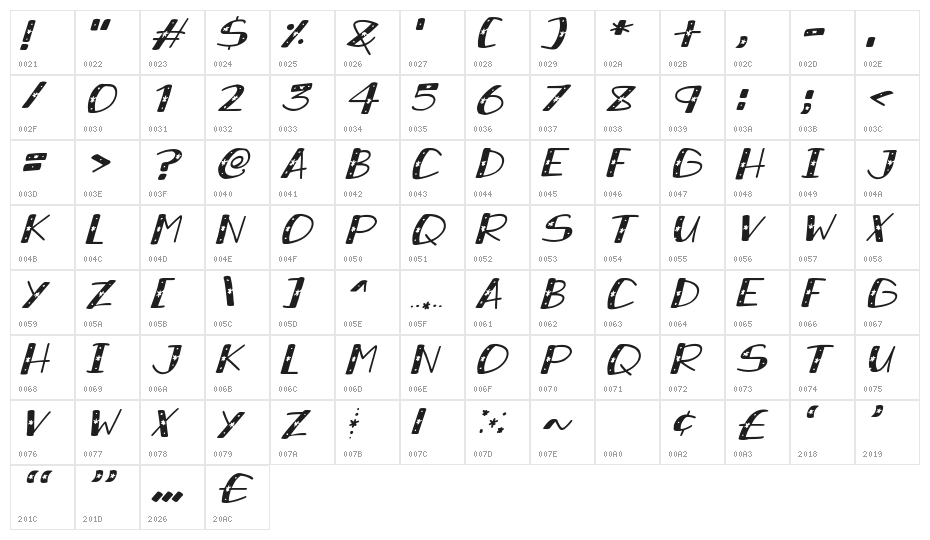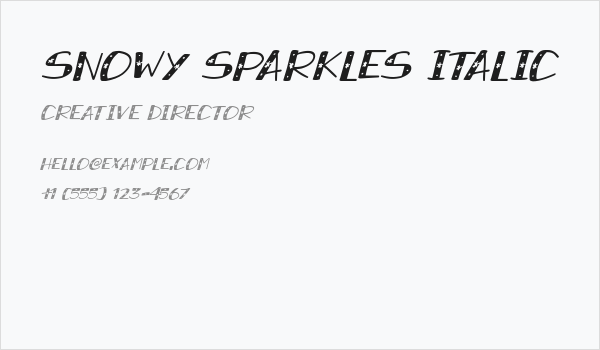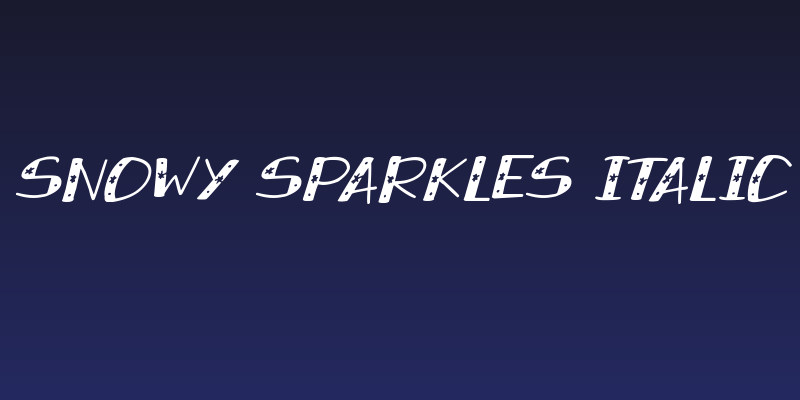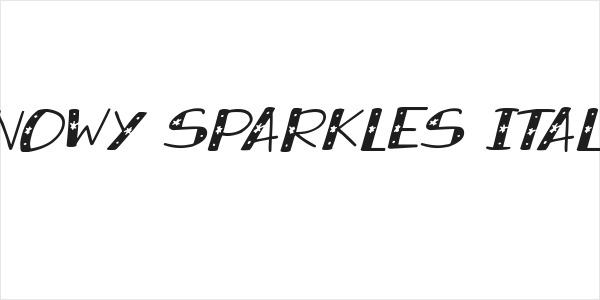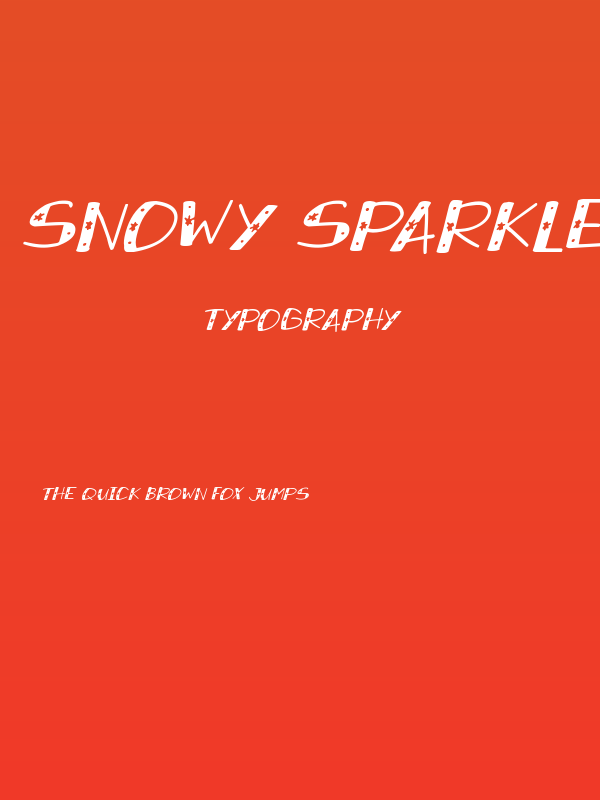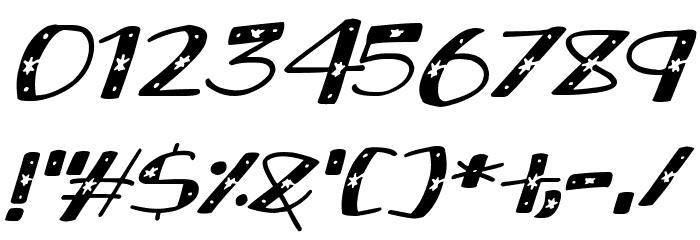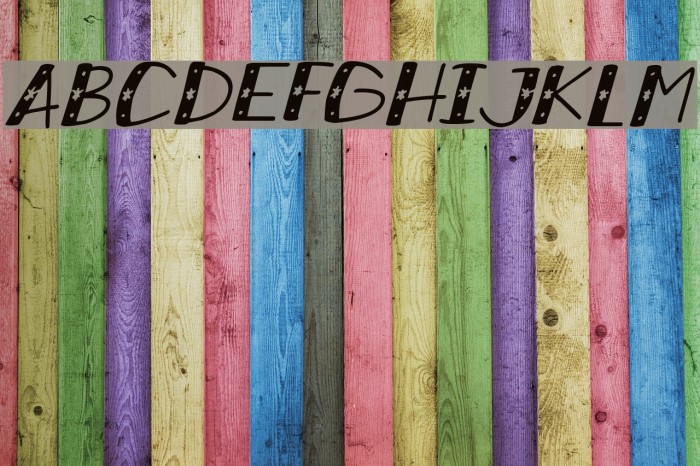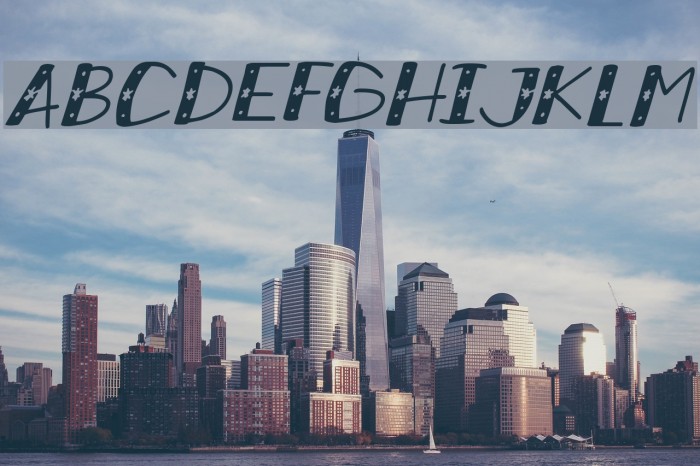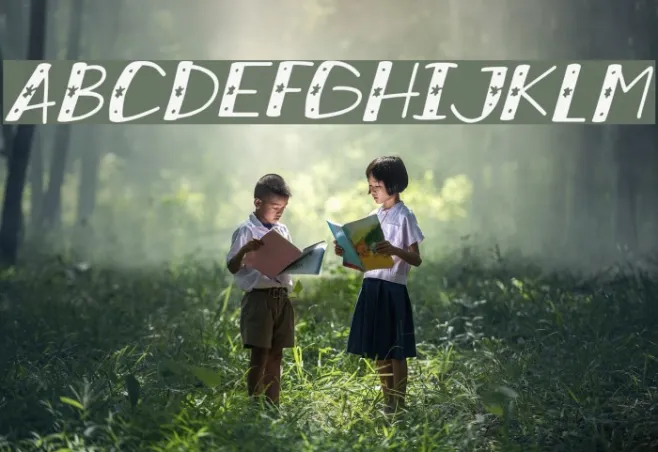
Snowy Sparkles Italic Font
Darrell Flood
| Schriften Familie | Snowy Sparkles |
| Anwendungsfall | Headlines, Logos, Invitations |
| Vorgeschlagene Projekte | Ideal for holiday cards, party invitations, children's book covers, or any project needing a magical touch. |
Darrell Flood